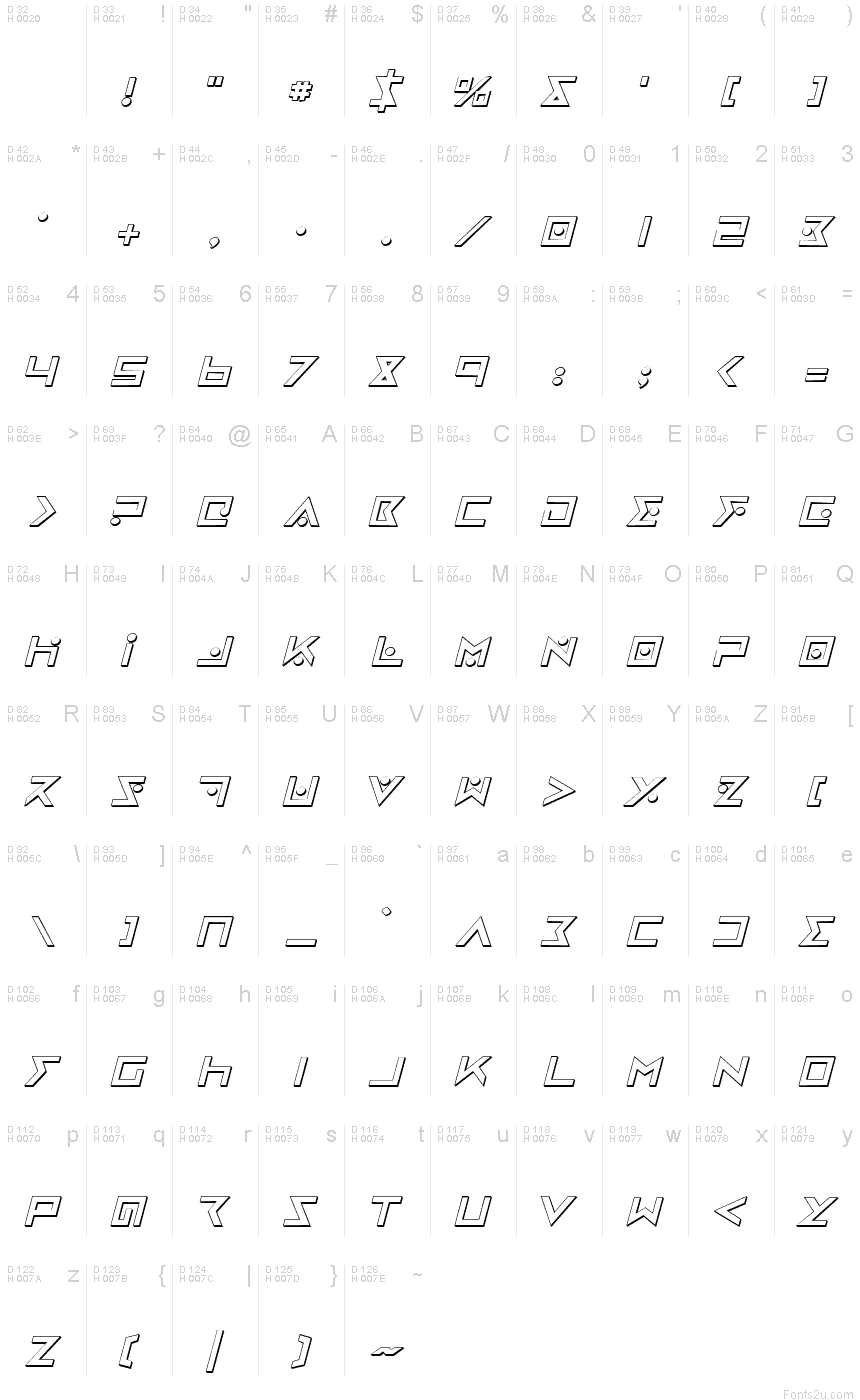
Iron Cobra 3D Italic od Iconian Fonts to darmowy techniczny krój wyświetlaniowy 3D o ostrym, dynamicznym charakterze. Kanciaste litery, otwarte wnętrza i przesunięte detale konturów przywodzą na myśl inżynieryjne panele w ruchu.
Wyraźne pochylenie nadaje szybkości i napięcia logotypom e-sportowym oraz ekranom tytułowym gier wyścigowych. Ten darmowy font świetnie sprawdzi się w opakowaniach science-fiction, plakatach sportów motorowych i grafikach streamingowych, nadając im mechaniczny klimat w stylu arcade, a jego trójwymiarowe krawędzie sprawiają, że litery świetnie współgrają z metalicznymi teksturami i futurystyczną oprawą wizualną.
Iron Cobra 3D Italic